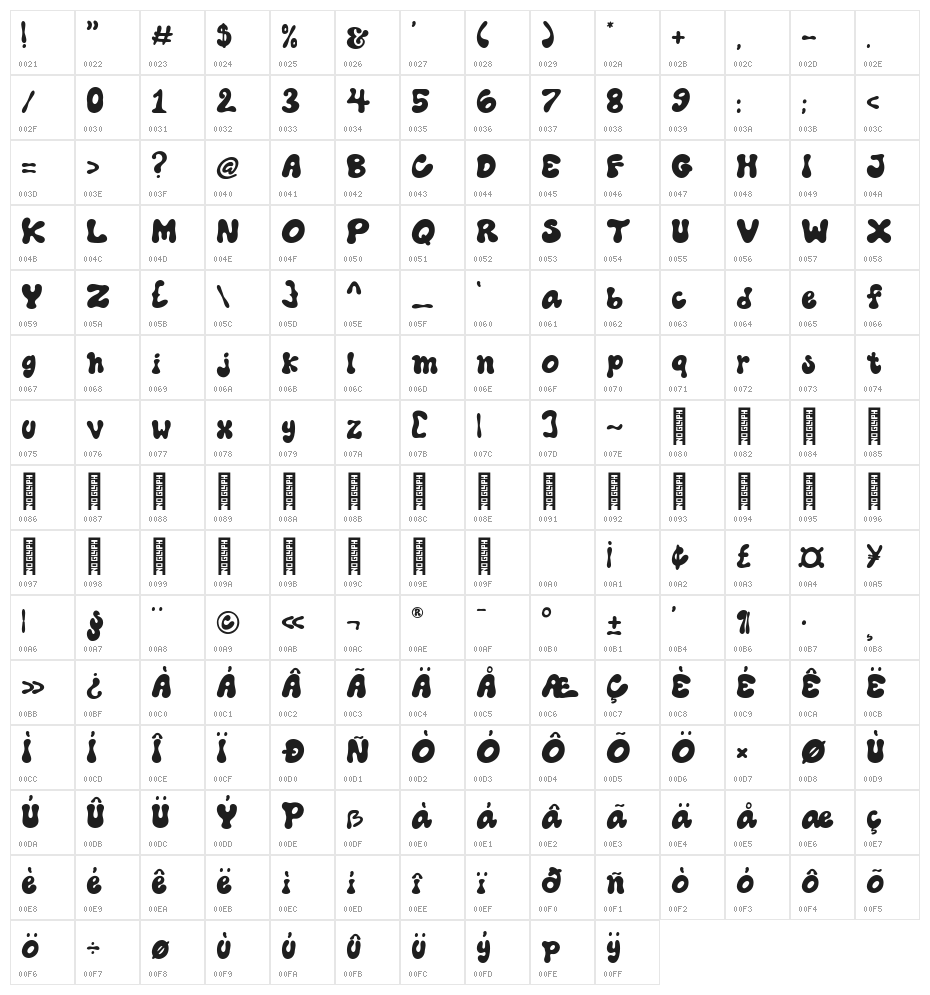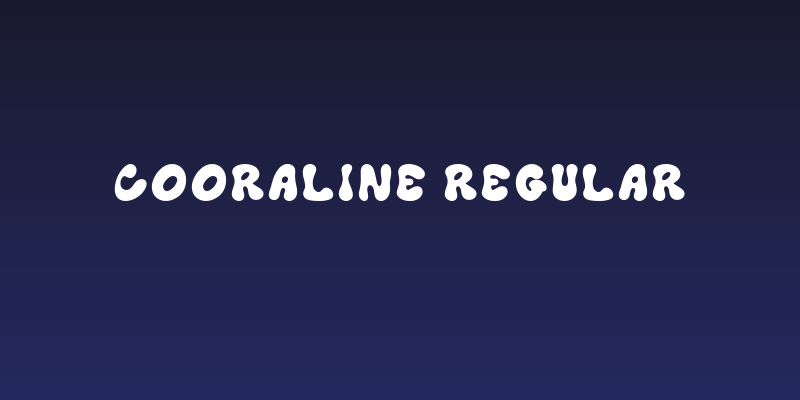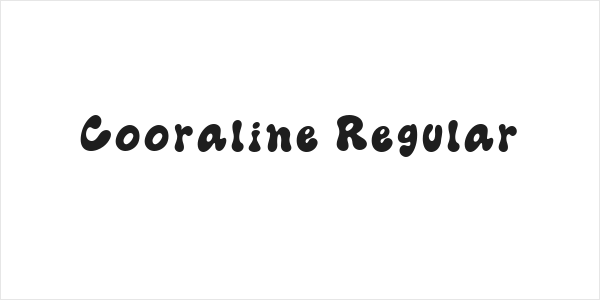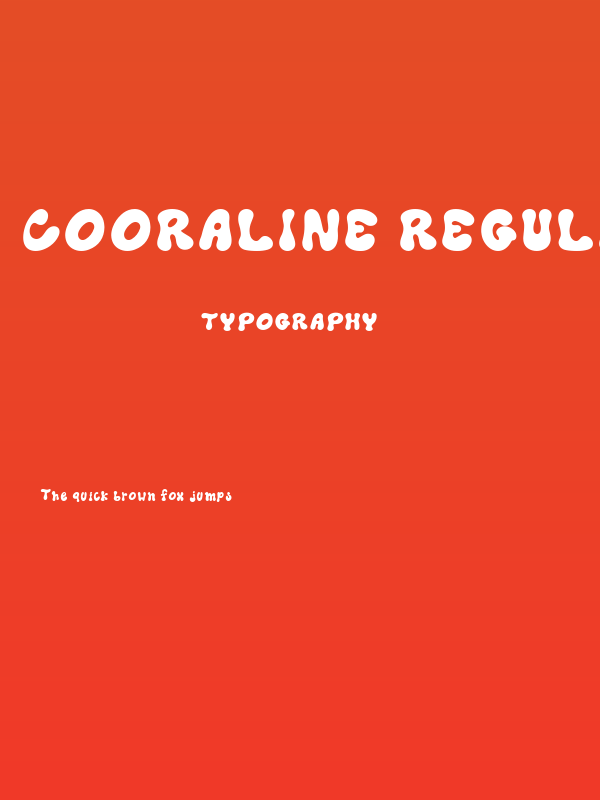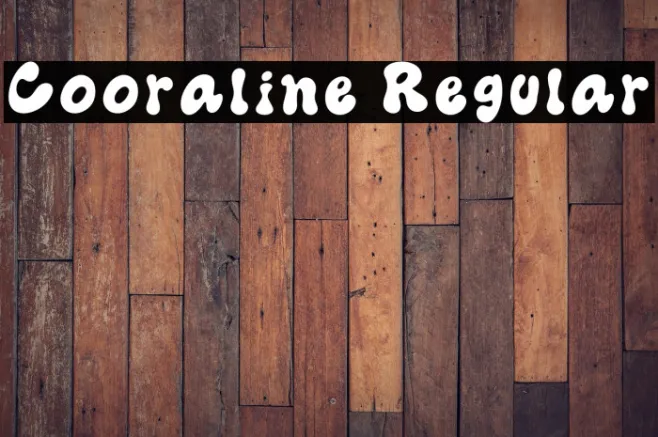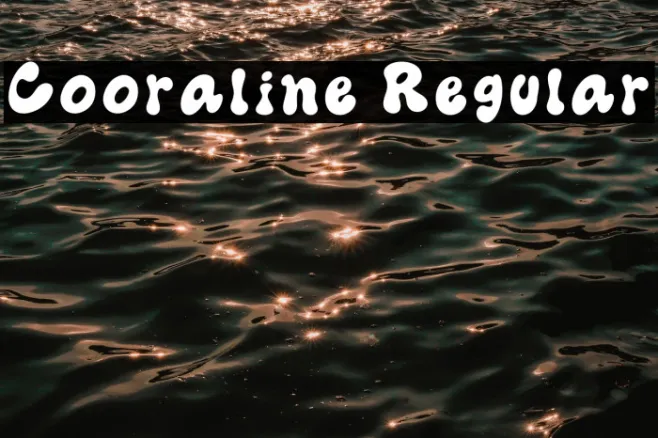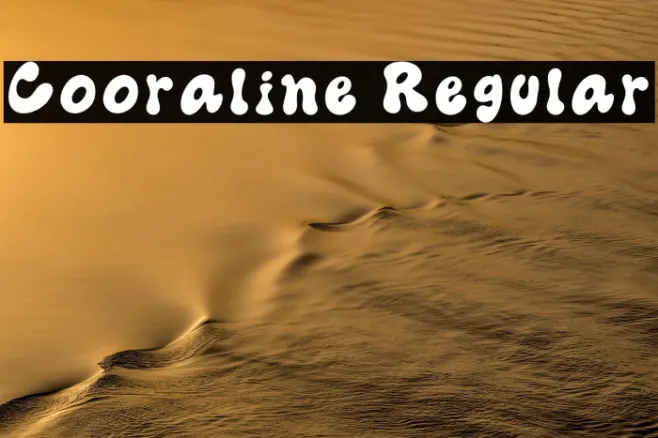
Cooraline Regular Font
| Gesamtstil | Playful, Whimsical |
| Vorgeschlagene Projekte | Ideal for children's books, playful branding, party invitations, and creative posters. |